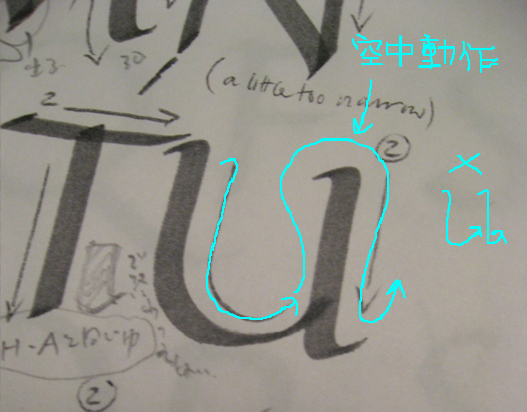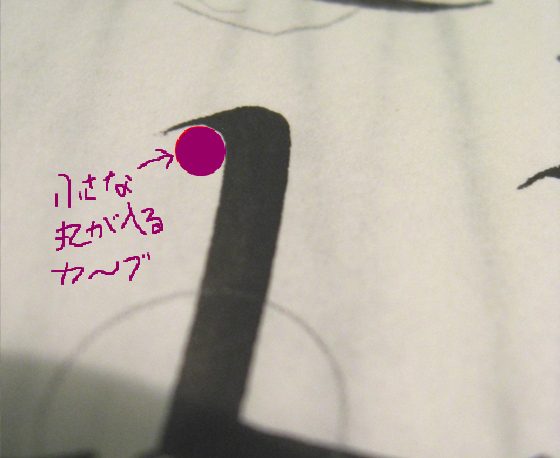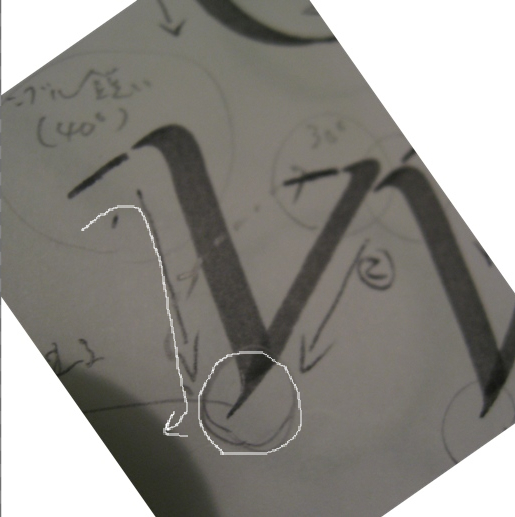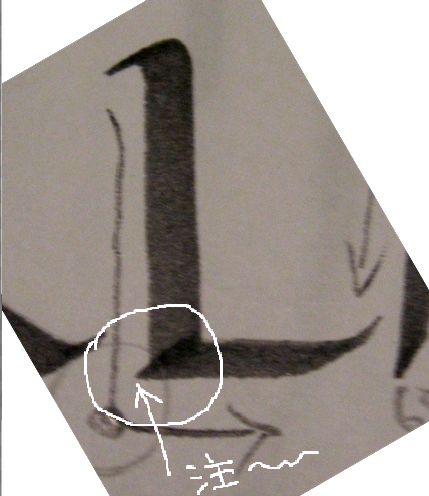
Finding Enjoyment in Writing 続き
ストロークの始まりはとても注意深く
…。これは伝統的なサンプルなので、細いラインが書けるよう心掛けます。
Lの縦ラインから横に入る角です。
これは不思議な体験で学びました。
この突起のような角を出すには、
無理やり作るのではなく、
縦ラインが下りきった所で一呼吸置きます。
そうすると、持ち手の緊張が緩み一瞬ペンが戻ろうとするのです。抑圧から解放されて
「ふぅ〜。」って言ってるみたいな感じです。なので自分でわざと戻してはいけないのです。
実践してみると不思議な気持ちになります。「あ〜自然にこの形になるんだ〜」と。
そして角は90度ではなく、もうわずかですが90度より広いのです。そういう見えるか見えない
くらいの広がりが目に優しいそうです。
このLを書く様子をEwanは言葉で表現してくれます。
「蜘蛛が上って、スーと糸を垂らして下りてくる。止まって…スタスタ…逃げる」みたいな…。(笑)
それを頭で描きながら書く練習をします。するととても心地よいリズムで書けるのです。
Uは、左側を書いて右を書くとき、一本調子で書きません。
円を内在する文字と同じように空中でカーブを描きながら
右側の始めに入ります。
Uの中の空間にもエネルギーが入り込むんですね…。
すご〜い。
これも衝撃…。
V,W,Mなどの交差する部分です。
この重なりがうまくいかないと、ボッテリなことに
なってしまいますねぇ…(涙)
これは左からくるストロークの最後にわずかに
左へはらうというかはねるというか…。
こうするろ右からのストロークが重なったときに、
シャープな形が保てるそうです。
Ewanは、Ann Campの教え子ですから、Annのプロポーションで教えてくれます。
たいていは、Sheilaの方法で、正方形の中に円を書き、その正方形に対角線を引き、円の弧と交わる縦線が長方形(AとかHとか)グループとなり、比率は全体の四分の三になりますが、Annは、
円を先に書くんですね…。図に書かないとわかりにくいのですが、円をかいて長方形で囲むので、
長方形の比率が四分の三より少し広くなるのです。まぁこれは好みにもよりますね。
(この比率の差は、nibの太さで影響してきます。)
でも一番の醍醐味は、Ewanが聞いた話しからの構造の学ぶ方法です。
仏像の描き方を教える方法の一つに、身体のパーツを取り込んだ詩を暗記することで
覚える方法があるんだそうです。そこから幾何学で覚えるだけではない方法をEwanも
見つけたのだそうです。
昔の修道院でも文字の構造を説明している詩があったそうです。
そういうものを見つけて、Ewan自身が各アルファベットのストーリーを作れるようになった
そうです。
「W」を書くときのお話しです。
1. Dusk 2.pink evening 3. an ink-stroke pine 4. a single star
さぁ、この1〜4はWの書き順でもあります。この1〜4の言葉を思いながらWを書いて
みてくださいねぇ。
1たそがれのストローク、2夕焼けが美しいストローク、3夕焼けが暗くなり影だけが存在
してくるストローク、4光が見える…光はだんだん下りてくる
時間まで流れていますねぇ。
こんな風に感情を込めながら文字を練習できたら本当に楽しいですねぇ!
そして、後半三日間のhは、泣き虫カリグラファーになりました。
また後日…。
「たそがれのストローク」ってなんだろう??って謎ですが、
なんとなく分かるような気もするのが不思議です。
昔の人は、イメージや言葉を、場所に結びつけて記憶したそうですが、
(回廊を歩くことで聖書を記憶するとか)
理屈じゃないんですね〜
RomanCapsのひとつひとつ、本当に丁寧に気持ちを入れて書いていましたね... 今までもそれなりに、丁寧に書いていたつもりだったけど、指摘されるたびに...あ〜〜!!! と気付かされて。楽しかったーー!またWS、ご一緒しましょう!
奈良さんならA to Zですが、EwanならA to Z 絵描きうた
…とでもなるでしょうか…。
「B」は、BASHOからとってきて、
1.journey's end 2.rising mist 3.rising moon
だったんです。Bのお腹は「朧月夜」だなんて!
秋の夜長は「B」ビーーーです!
本当に今でも思い出し笑いしてしまいます。
Ewanの蜘蛛ジェスチャー〜。
書くということ自体を本当に愛おしいと思わせて
くれるEwan!良い人だぁ〜。またご一緒に!
zizisさんのプロジェクトも本当に美しかったです!
きっと次の作品では…楽しみです!